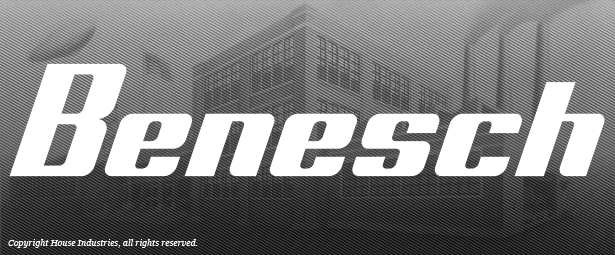
Schriftart von einer Rechnung
leider habe ich außer der Grafik keine Informationen zu der Schrift.
Wäre aber schön wenn Ihr mir als Experten sagen könntet wie man die Schrift nennt oder wo ich einen möglich ähnlichen Font finden könnte.
die hier wäre ähnlicher, hätte aber immer noch falsche n und h:
Und ich kann sie nirgendwo in den Läden finden ...
MyFonts WhatTheFont lieferte gar nichts brauchbares ...
Ok, da gäbe es die aufrechte Orbitron, auch mit falschen n und h:
Ich dachte zuerst: Die sollte leicht zu finden sein ... :-?
Mit der Bullet komme ich super hin.